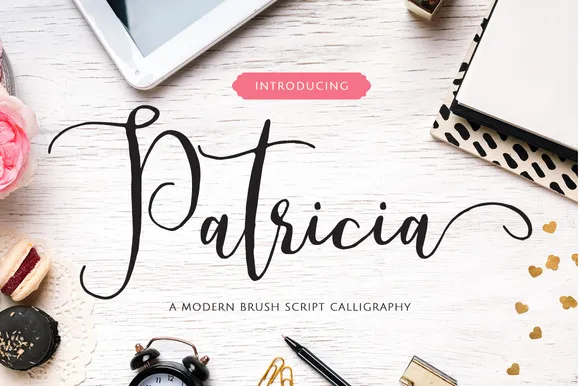
Descubra a elegância inspiradora de Patricia Script Font na categoria de fonts script! Inspirada por uma mão real, essa nova opção para designer oferece precisão e beleza em projetos que necessitam de um toque sofisticado. Patricia é perfeita para diversos tipos de design, como criação de logomarca, identidade visual, gráficos do blog, estilização de citações, embalagens, materiais de marketing, anúncios nas redes sociais e muito mais. Seja você um artista ou designer de blogs, essa font é sua nova parceira para projetos elegantes e atraentes. Descubra como Patricia pode moldar seu design!